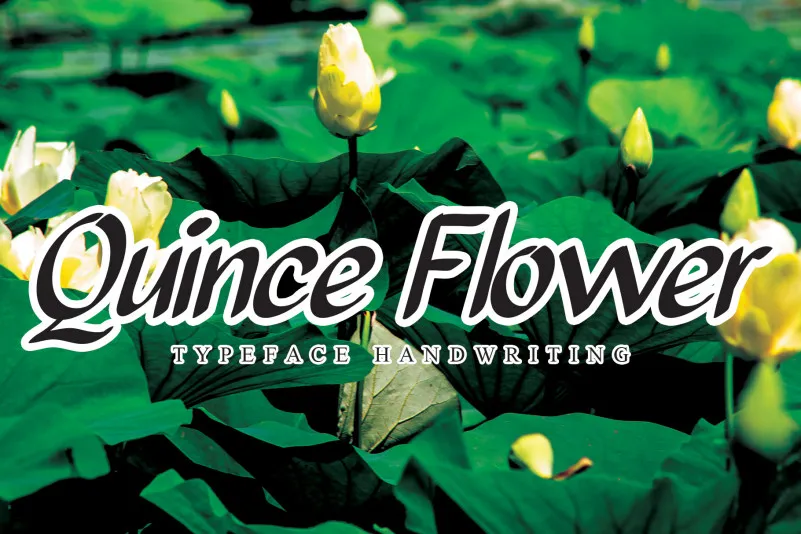
Quince Flower Brush Font – Fonte Grátis
Quince Flower Brush Font
A Quince Flower Brush Font é uma fonte que captura a magia do desenho à mão. Com seu estilo clássico impecável, mantém uma sensação amigável e receptiva. Ideal para criar designs originais e impressionantes, essa fonte se destaca na categoria de fontes escrita. Combinando elegância com simplicidade, a Quince Flower é uma escolha perfeita tanto para projetos pessoais quanto profissionais. Se você busca um toque único que capta o espírito da arte manual, esta fonte será certamente sua amiga no processo de design.